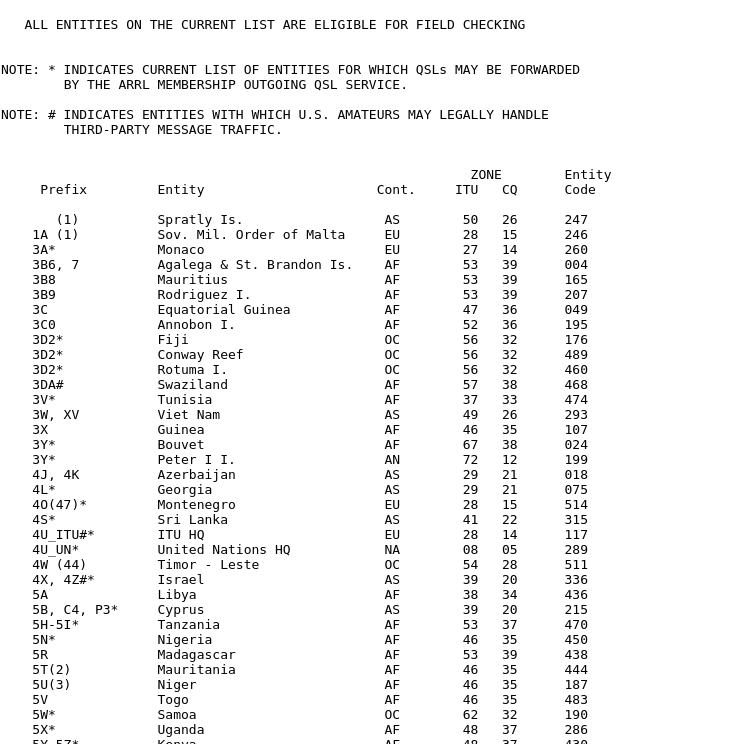
Schriftart für ein Tabellenbuch
Ich bin dabei ein Tabellenbuch zusammen zustellen. Das Buch soll nach Möglcihkeit in die Hosentasche passen. Ich denke DIN A6 ist die richtige Größe. Es sind circa 400 Seiten.. Zum Inhalt sei gesagt, viele Zahlen und Tabellen. Einige Formel und viel Text und Fußnoten.
Meine Fragen sind:
1. Welche Schriftart sollte ich wählen? Welche Schriftgröße, Randbreite, Bundsteg.  Hat jemand eine Skizze von so einem Buch?
2. Ist Latex eine gute Wahl? Wie ist Eure Empfehlung? Hat jemand ein Latex Template?
3. Ist eine PDF Datei das richtige Format für eine Druckerei?
Zu Schrift, Layout und Satzprogramm kann ich ohne den Inhalt zu kennen nichts sagen. Es klingt aber nicht ganz trivial und du solltest dir auf jeden Fall gestalterischen Rat holen. Wenn das Budget nicht für eine professionelle Umsetzung reicht könnte ein Grafiker eventuell ein Template (zu überschaubaren Kosten) anlegen dass du dann befüllst. Bei 400 Seiten ist der Grundaufbau relativ wichtig da späte Änderungen sonst sehr viel Aufwand verursachen (Seitenzahlen, automatisches Inhaltsverzeichnis, ...).
Die verwendet Schrift sollten auf jeden Fall Tabellenziffern und den entsprechenden Zeichenumfang für die Formeln mitbringen.
Zeig doch mal ein paar Inhalte und sag uns für wen das Buch gedacht ist und warum du es erstellen willst.
Je nach Papiervolumen wird das schon hübsch dick – mit einem Soporset 80 g/m² (1,3-fach) kommen 400 Seiten auf ca. 21 mm.
Ich würde eine halbwegs schmal laufende Schrift nehmen, damit sparst du Seiten bzw. schaffst notwendige Weißräume. Für eine erste Orientierung sind die medizinischen Kitteltaschenbücher gut geeignet, da ist viel Inhalt in ein kleines Format gebracht.
Zur Zeit habe ich nur Text Dateien geliefert bekommen. Ich habe einen Screenshot mit einer Tabelle angehängt. Die Formeln habe ich mithilfe von Latex gesetzt. So können die Tabellen natürlcih nicht bleiben.
Das weckt unangenehme Erinnerungen an Geographie-Klausuren (Weltalmanach, CIA World Factbook, Länderberichte der Banken)... Das willst Du wirklich in A6 bringen? Da wirst Du wohl echt Profis brauchen, damit da eine übersichtliche Lesbarkeit entsteht. Ich fand diese Listen bereits in A5 mühselig und habe mit Linealen arbeiten müssen, um nicht ständig Sorge zu haben, verrutscht zu sein.
Ich denke man bekommt das mit entsprechendem Aufwand auch in A6 halbwegs übersichtlich hin – es wird dann aber viele Tabellen geben die über mehrere Seiten laufen. Bei einer Klebebindung in dieser Größe verliert man zudem auch viel Platz zum Bund hin. A5 oder minimal größer (165 x 220) wäre sicher günstiger. Das Argument mit der Hosentasche ist bei 400 Seiten ja wie gesagt schon obsolet …
deine fragen 1 bis 3 lassen vermuten, dass du im erstellen von printprodukten nicht der erfahrendste bist. sich diese vielfältigen fertigkeiten aneignen zu wollen finde ich sehr löblich. dass du aber sogar die basics von satz und reinzeichnung gleich anhand eines derartigen monsterprojektes angehen willst lässt bei mir – stellvertretend für dich – die alarmglocken schrillen. ich rate dir dringendst, dich einem profi anzuvertrauen! wenn man nicht ganz genau weiß was man tut, kann sich ein solches projekt schnell zum alptraum entwickeln. (außer natürlich das wird dein neues hobby und du hast jede menge zeit, geld und nerven und gerade ohnehin nichts besseres zu tun.)
Nun, bei  400 Seiten A6 denke ich, hier sollte man mal nach Bibeldruckpapier fragen. Ich habe da gerade ein Exemplar mit fast 1400 Seiten, und das kommt bei etwas kleiner als A6  auf hosentaschentaugliche  23mm, das bedeutet, 400 Seiten kommen damit grad auf 7mm.
Aber wichtig bei den Tabellen, dass man eine Hilfe hat, den Zeilen zu folgen,also Hilfslinien oder ein zarter Hinterdruck z.B. für je 3 Zeilen einplanen.
Ich erinnere mich auch, in der Zeit vor Internet und Containern gab es in Hamburg ein jährlich erscheinendes Adress-Taschenbuch mit ähnlicher Seitenzahl. Auch das war auf Dünndruckpapier und sogar nur Drahtgeheftet. Wie die das hin bekommen haben, dass sich da so ein perfekter Halbkreisrücken geformt hat, ist mir ein Rätsel.
Hast du ein Budget für Schriften oder brauchst du welche, die entweder schon bei einem Programm oder Betriebssystem mitgeliefert wurden, oder die (legal) kostenlos verwendet werden können?
Ich würde nach Dünndruckpapier fragen, das wird gerne z.B. für Bibeln und Gesangsbücher (Gotteslob etc.) verwendet. Und achte auf Registerhaltigkeit, damit durchscheinende Buchstaben von der Rückseite des Papiers weniger stören.